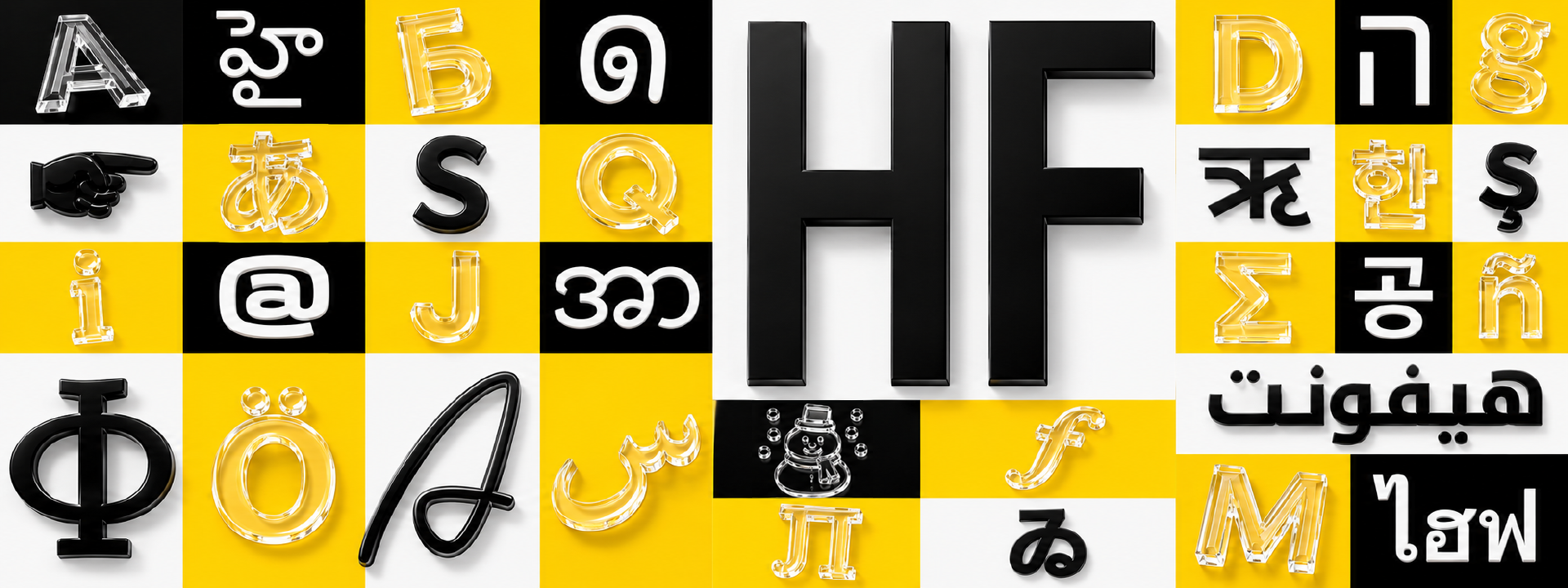
由 HyFont 设计中心精心打造的多语种字体新作
一款现代实用的人文主义无衬线字体。其笔画结构清晰均衡,倒角利落。整体造型简约而不失温度,非常适合各类数字化界面与纸媒的正文及标题排版。
支持 5 种字重 / 21 种书写系统
一款基于几何网格构成的极简无衬线字体,线条干净且富有理性节奏,适配现代感科技网页、实验性视觉设计与工业风品牌识别。
一款方正厚重的粗体无衬线字体,适配强冲击力海报、品牌主标题与力量感视觉设计。
一款流畅随性的手写风格无衬线字体,适配文艺风文案、手账设计与轻松治愈系视觉项目。